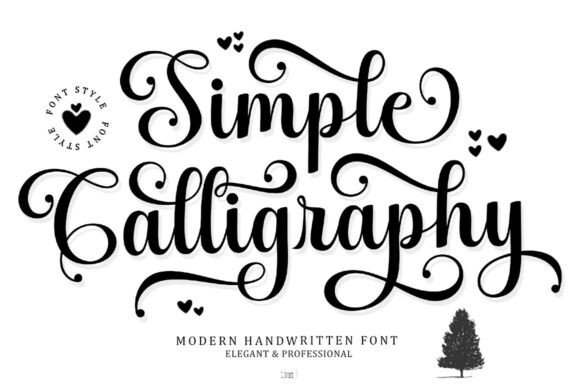
Simple Calligraphy
Die richtigen Designelemente zu finden, kann eine Herausforderung sein, aber Simple Calligraphy bietet eine außergewöhnliche Sammlung, die Ihre Arbeit sofort aufwertet.
Egal, ob Sie POD-Produkte (Print on Demand), Hochzeitseinladungen oder Social-Media-Grafiken erstellen, Simple Calligraphy ist die ideale Wahl.